Artikel ini menyajikan 14 font tulisan Cina atau aksara Tionghoa gratis, baik yang berbentuk tradisional maupun yang sederhana.
Font Aksara China Sederhana (Aksara Han Sederhana)
Aksara Han sederhana atau Hanzi sederhana digunakan di Tiongkok, Singapura, dan Malaysia.
Liu Jian Mao Cao – Font Kaligrafi Cina Tradisional
Font ini menampilkan gaya kaligrafi kuas tradisional Cina, cocok untuk desain poster budaya, undangan, atau karya seni bertema oriental.
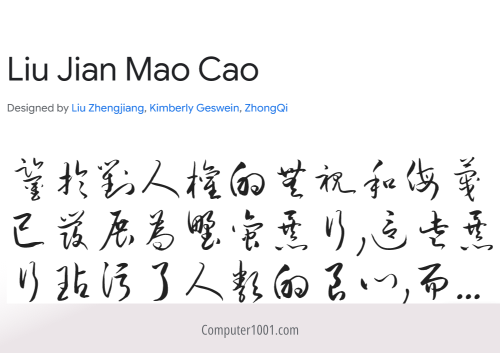
Long Cang – Font Kaligrafi Tulisan Tangan Cina
Font kaligrafi Cina yang mirip tulisan tangan anak-anak. Font ini cocok untuk anda yang ingin membuat kartu ucapan tahun baru imlek, postingan di sosial media, atau desain lain dengan aksen playful namun artistik.
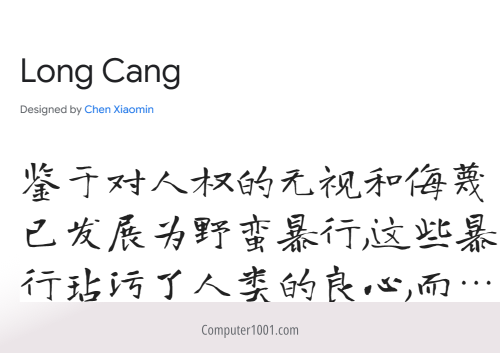
Ma Shan Zheng – Font Tulisan Tangan Cina
Font mirip tulisan tangan yang memiliki gaya cetak tebal. Cocok digunakan untuk membuat poster danchun Lian / dui lian, yaitu rangkaian kata-kata yang biasanya ditempel di dinding atau samping pintu saat perayaan Imlek; catatan pribadi, desain kreatif, dan konten edukasi lainnya.
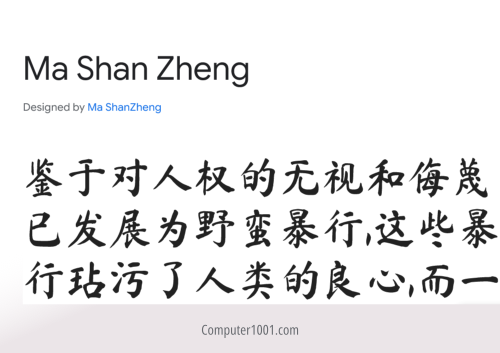
Noto Sans Simplified Chinese – Font Sans Serif Cina Modern
Font sans serif elegan, ideal untuk presentasi formal, dokumen akademik, dan branding bisnis. Font ini memiliki beberapa ketebalan, mulai dari yang tipis 100 sampai dengan ketebalan 900.
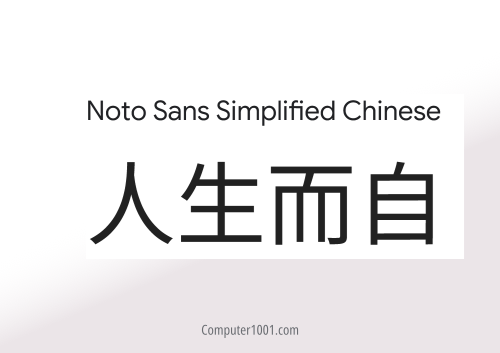
Noto Serif Simplified Chinese – Font Serif Cina Sederhana
Font serif aksara Cina Hanzi sederhana yang memiliki ketebalan 200 sampai dengan ekstra tebal 900. Font serif elegan ini ideal untuk presentasi formal, dokumen akademik, dan branding bisnis.
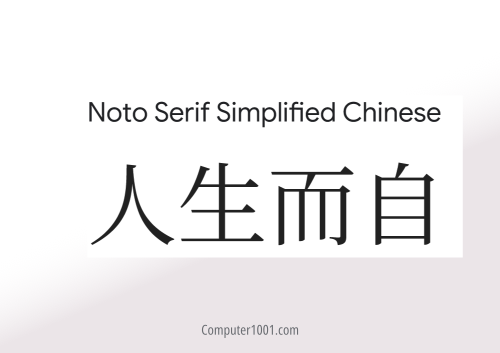
ZCOOL QingKe HuangYou – Font Display Cina Unik
Font display dengan karakter unik, sering dipakai untuk judul besar dan poster digital. Font ini memiliki bentuk karakter yang tinggi dan tebal, dengan bagian ujung yang bulat.
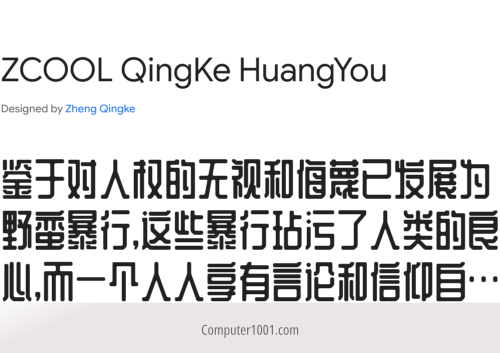
ZCOOL KuaiLe – Font Fun Display Cina
Font playful tulisan tangan dengan goresan yang tebal, cocok untuk desain anak-anak dan event kreatif.
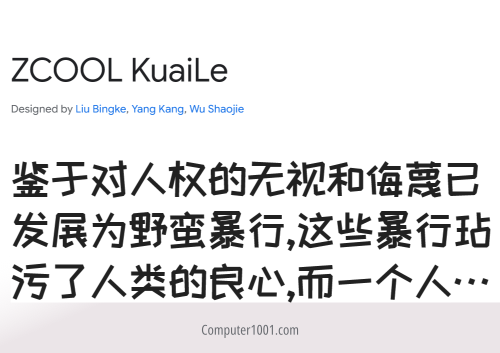
Zhi Mang Xing – Font Tulisan Kuas Semi-Kursif Cina
Zhi Mang adalah aksara klasik yang didasarkan pada kaligrafi tulisan tangan. Memiliki gaya semi-kursif dimana goresan-goresan dalam karakter saling menyatu, tetapi karakter-karakternya sendiri tetap terpisah. Font kuas ekspresif ini cocok untuk desain bertema tradisional dan seni kaligrafi digital.
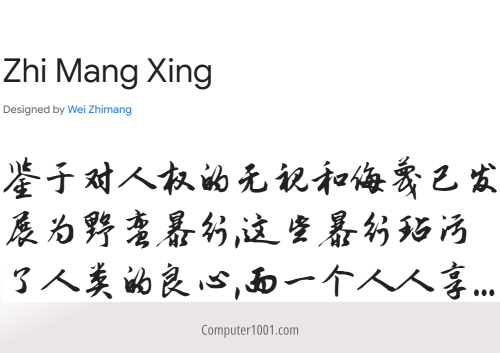
Font Aksara China Tradisional (Aksara Han Tradisional)
Aksara Han tradisional atau Hanzi tradisional umumnya digunakan di Taiwan, Hong Kong, dan Makau.
Cactus Classical Serif – Font Serif Cina Modern
Font tulisan Mandarin tradisional yang memiliki bentuk serif, seperti yang digunakan media cetak koran atau buku. Font ini cocok untuk berbagai desain formal dan branding bisnis.
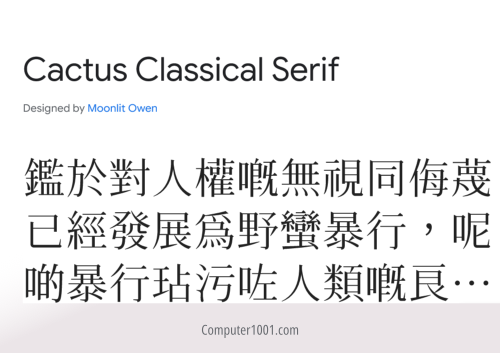
Chocolate Classical Sans – Font Sans Serif Cina Tebal
Font aksara Cina tradisional sans serif yang memiliki goresan warna yang lebih gelap. Cocok untuk berbagai desain formal atau bisnis.
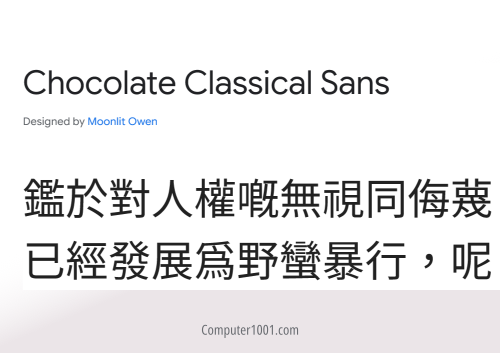
LXGW WenKai Mono TC – Font Kaligrafi Cina Monospace
Font tulisan Cina monospace, dimana setiap karakter memiliki lebar yang sama. Font ini memiliki ketebalan mulai dari 300 hingga 700. Font kaligrafi ini memiliki tampilan gaya tulisan tangan yang kasual dan kekinian.
LXGW WenKai TC – Font Tulisan Tangan Imut Cina
Font tulisan tangan serbaguna yang juga memiliki 3 ketebalan, dengan gorean ujung yang runcing seperti aksara pada buku pelajaran Mandarin. Bentuknya yang playful dan imut membuatnya ideal untuk proyek desain bertema anak-anak maupun remaja.
Noto Sans Traditional Chinese Font– Font Sans Serif Tebal Cina
Font sans serif modern dengan readability tinggi, ideal untuk poster dan presentasi formal atau bisnis. Font ini memiliki ketebalan tulisan mulai dari 100 sampai dengan 900.
Noto Serif Traditional Chinese Font – Font Serif Cina
Font Noto tulisan Mandarin tradisional versi serif, yang memiliki ketebalan dari 200 sampai dengan 900.